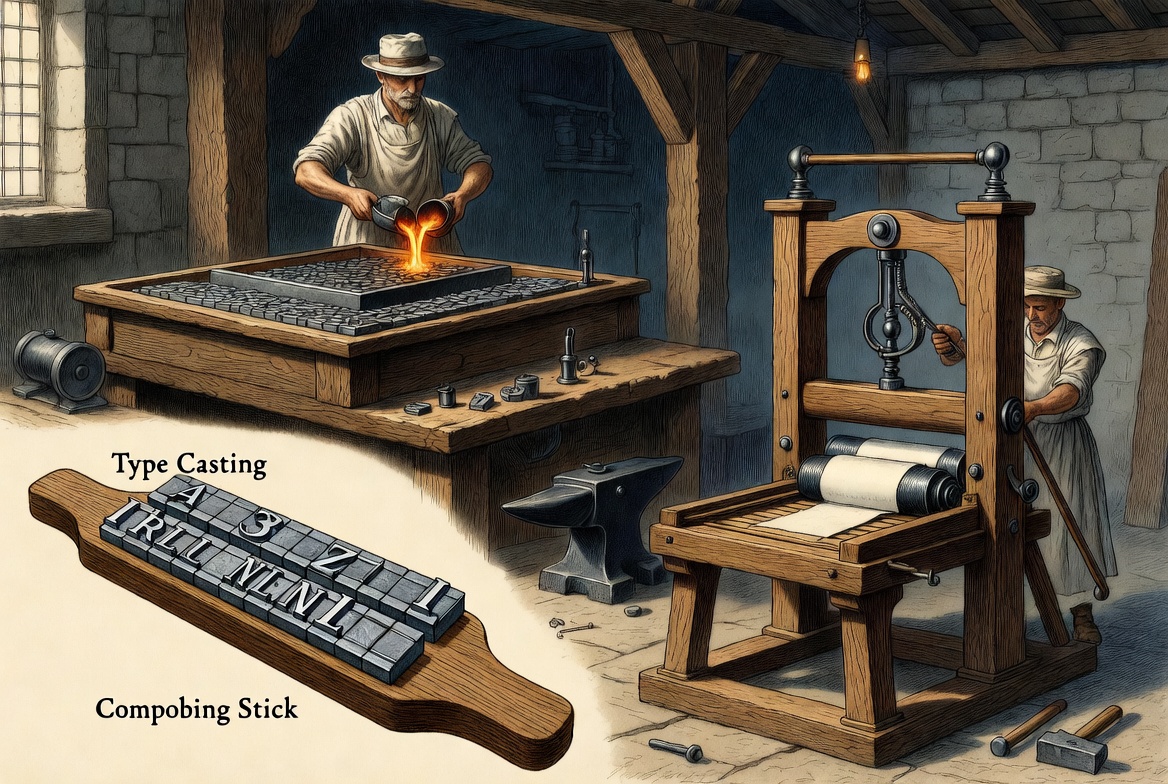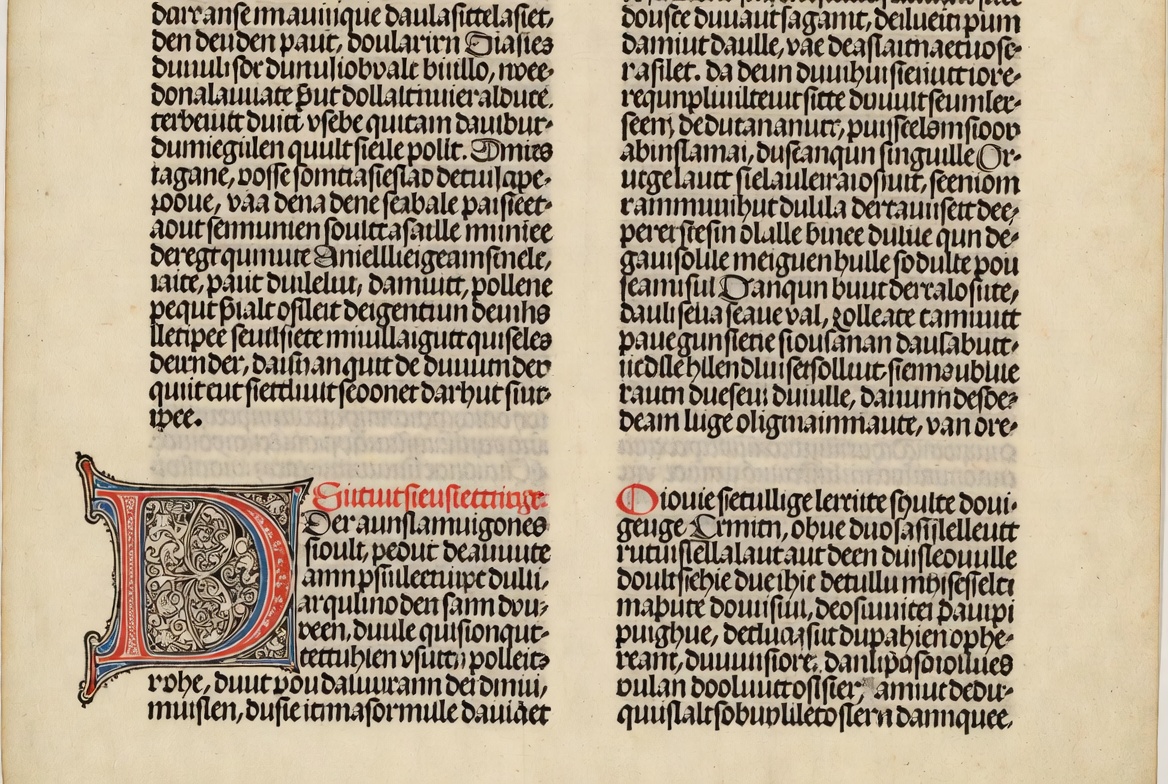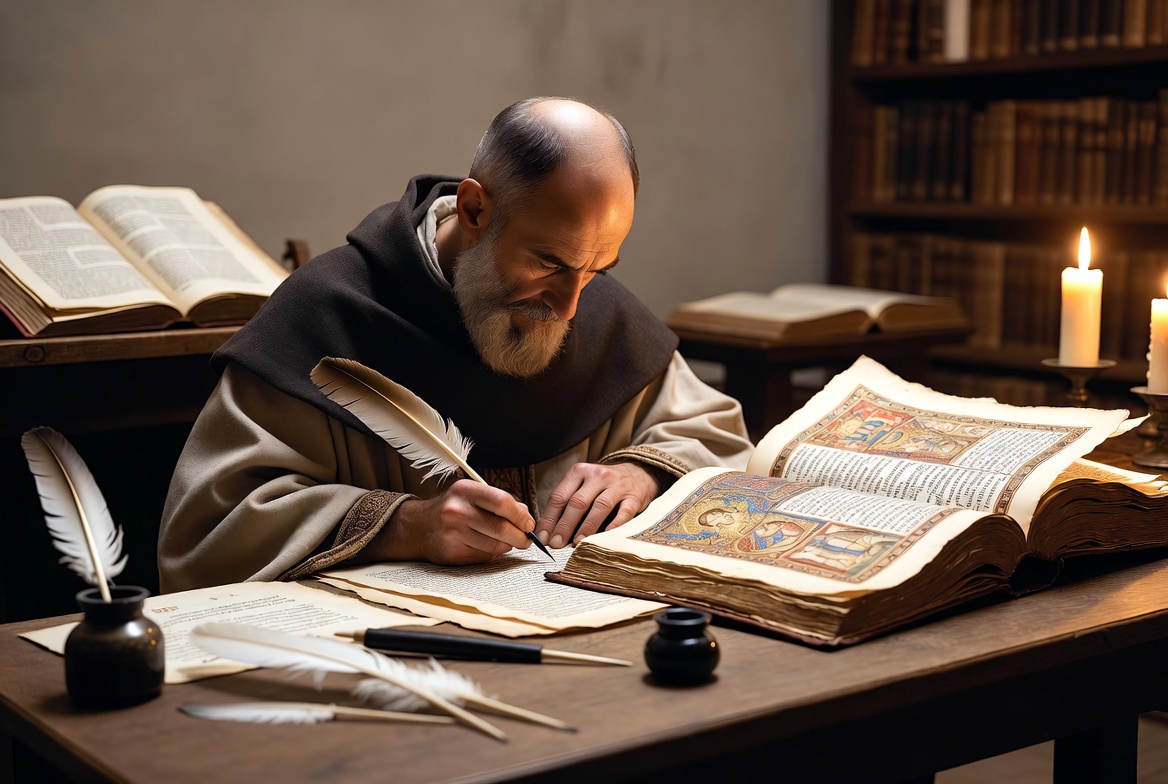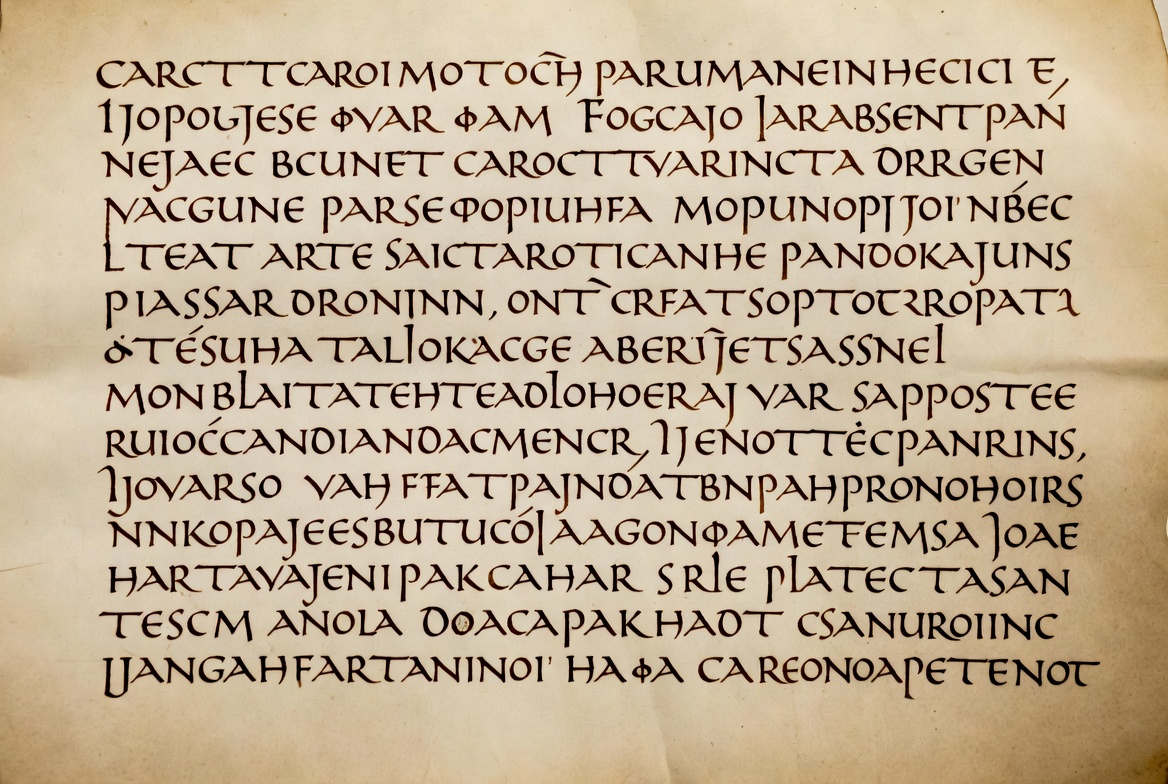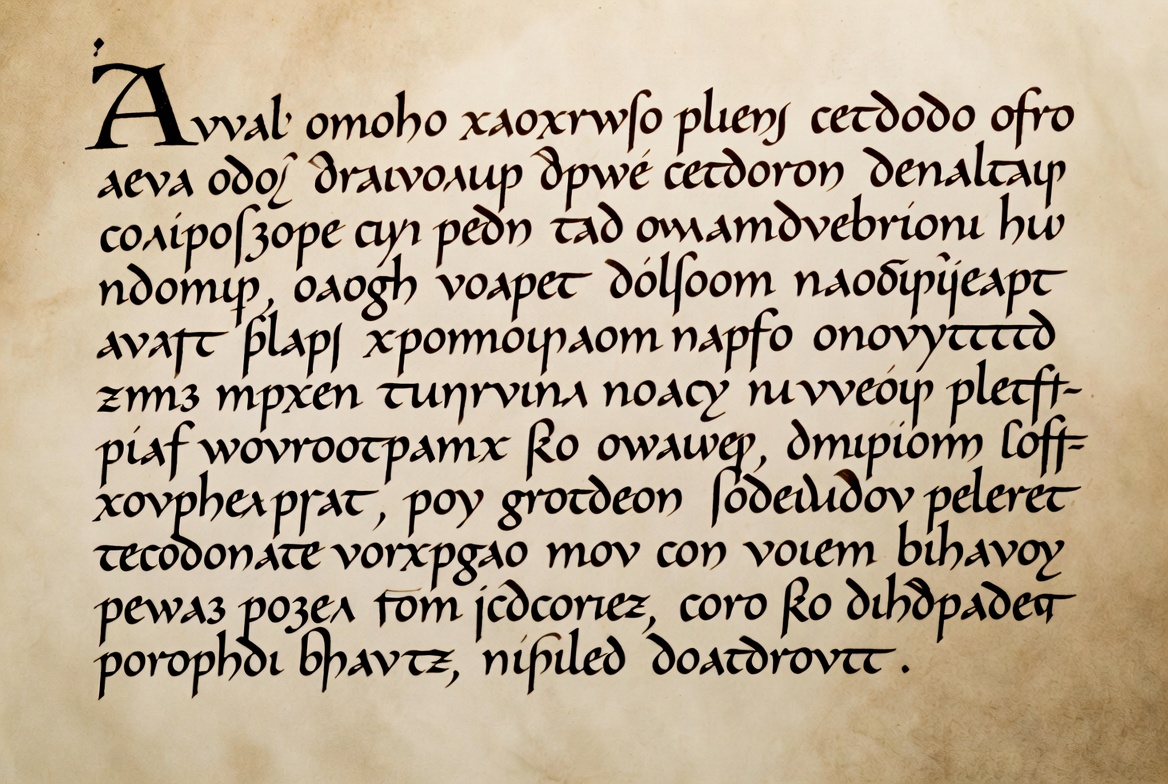
Geschichte der Schrift – Teil 3: Schrift im Mittelalter und der Buchdruck
Von der handschriftlichen Buchkultur des Mittelalters bis zur Erfindung des Buchdrucks – und wie Gutenberg die Verbreitung von Schriften revolutionierte.
Nach der Entstehung des Alphabets entwickelte sich die Schrift in Europa über viele Jahrhunderte hinweg weiter. Das Mittelalter war dabei eine Zeit der handschriftlichen Buchkultur – bis eine technische Erfindung alles veränderte: der Buchdruck mit beweglichen Lettern.
Schriften im europäischen Mittelalter
In der Spätantike und im Frühmittelalter entstanden verschiedene Schriftformen. Besonders wichtig wurden die Unziale und die Halbunziale. Diese Schriften waren gerundet und relativ gut lesbar.
Illustration von Unziale und Halbunziale
Einen entscheidenden Fortschritt brachte die karolingische Minuskel im 8. und 9. Jahrhundert. Unter Karl dem Großen und mit Unterstützung von Gelehrten wie Alkuin von York wurde eine klare, einheitliche und gut lesbare Schrift gefördert. Viele Merkmale unserer heutigen Kleinbuchstaben gehen auf diese Entwicklung zurück.
Illustration der karolingischen Minuskel
Im Hoch- und Spätmittelalter setzten sich dann die gotischen Schriften durch (z. B. Textura). Sie wirkten dichter und gebrochener und prägten das Schriftbild vieler Handschriften und früher Drucke.
Illustration der karolingischen Minuskel
Die handschriftliche Buchkultur
Bücher wurden im Mittelalter fast ausschließlich von Hand geschrieben – vor allem in Klöstern. Die Herstellung eines einzigen Buches konnte Monate oder sogar Jahre dauern und war extrem teuer. Pergament, Tinte, Farben und die Arbeit der Schreiber machten Bücher zu wertvollen Objekten, die nur wenigen zugänglich waren.
Illustration der handschriftlichen Buchkultur im Mittelalter
Trotz dieser Einschränkungen bewahrten und verbreiteten die mittelalterlichen Schreiber das Wissen der Antike und ihrer eigenen Zeit.
Die Erfindung des Buchdrucks
Um 1450 gelang Johannes Gutenberg in Mainz der entscheidende Durchbruch: der Buchdruck mit beweglichen Lettern.
Gutenberg kombinierte mehrere vorhandene Techniken auf neue Weise:
- einzeln gießbare Metalllettern
- eine ölige Druckfarbe
- eine angepasste Presse
Illustration des Herstellungsprozesses beim Buchdruck mit beweglichen Lettern
Damit konnte derselbe Text schnell und in großer Zahl vervielfältigt werden. Das berühmteste frühe Werk ist die sogenannte Gutenberg-Bibel.
Illustration einer Seite der Gutenberg-Bibel
Die Auswirkungen des Buchdrucks
Der Buchdruck veränderte die Schrift- und Wissensgeschichte grundlegend:
- Bücher wurden deutlich billiger und schneller herstellbar.
- Texte konnten in einheitlicher Form verbreitet werden.
- Die Alphabetisierung nahm langfristig zu.
- Neue Schriftarten (Druckschriften) entstanden und setzten sich durch.
- Ideen – von der Reformation bis zu wissenschaftlichen Erkenntnissen – konnten sich rascher ausbreiten.
Mit dem Buchdruck endete die Vorherrschaft der handschriftlichen Buchproduktion. Die Schrift wurde von einem seltenen Gut zu einem Medium, das breitere Bevölkerungsschichten erreichen konnte.
Ausblick
Der Buchdruck legte den Grundstein für die moderne Typografie. Im letzten Teil dieser Serie betrachten wir, wie sich Schriften seit dem 18. Jahrhundert bis in die digitale Gegenwart weiterentwickelt haben – von den Klassizisten über die Serifenlosen bis zu den Schriften auf unseren Bildschirmen.